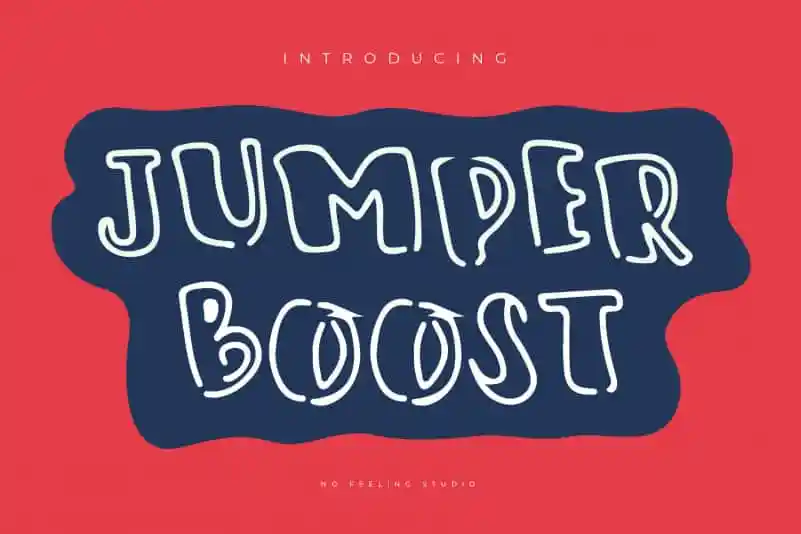
Jumper Boost Display Font – Download Grátis
A “Jumper Boost Display Font” é uma tipografia para impressão desenhada à mão com influência de bolhas de sabão. Inspirada no brilho vibrante e fluido das bolhas, esta fonte única se destaca por seu movimento elegante que flui naturalmente na superfície da página. Perfeita para projetos de marca, logomarcas, posters, capas de livros e posts em redes sociais, a “Jumper Boost Display Font” oferece uma maneira moderna e impactante de estilizar qualquer design visual. Com sua natureza vibrante e autêntica, esta fonte para impressão desfruta de seu charme decorativo e se adapta perfeitamente à criação de materiais de mídia social, como postagens em redes sociais que exigem um toque especial. Além disso, o design da “Jumper Boost Display Font” também pode ser usado em campanhas de marketing para criar uma identidade visual única e memorável. A fonte é perfeitamente adaptada a diversos projetos gráficos, garantindo não apenas funcionalidade prática, mas também um toque especial que faz deste o recurso de tipo ideal para designers que buscam expressar personalidade em seus trabalhos. É uma opção ideal tanto para novatos quanto para profissionais de design gráfico que procuram uma fonte única e vibrante para adicionar a sua coleção de tipos especiais.